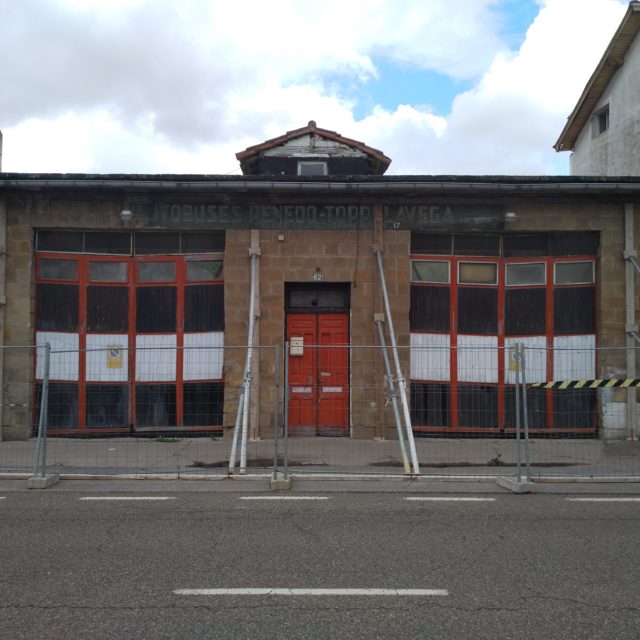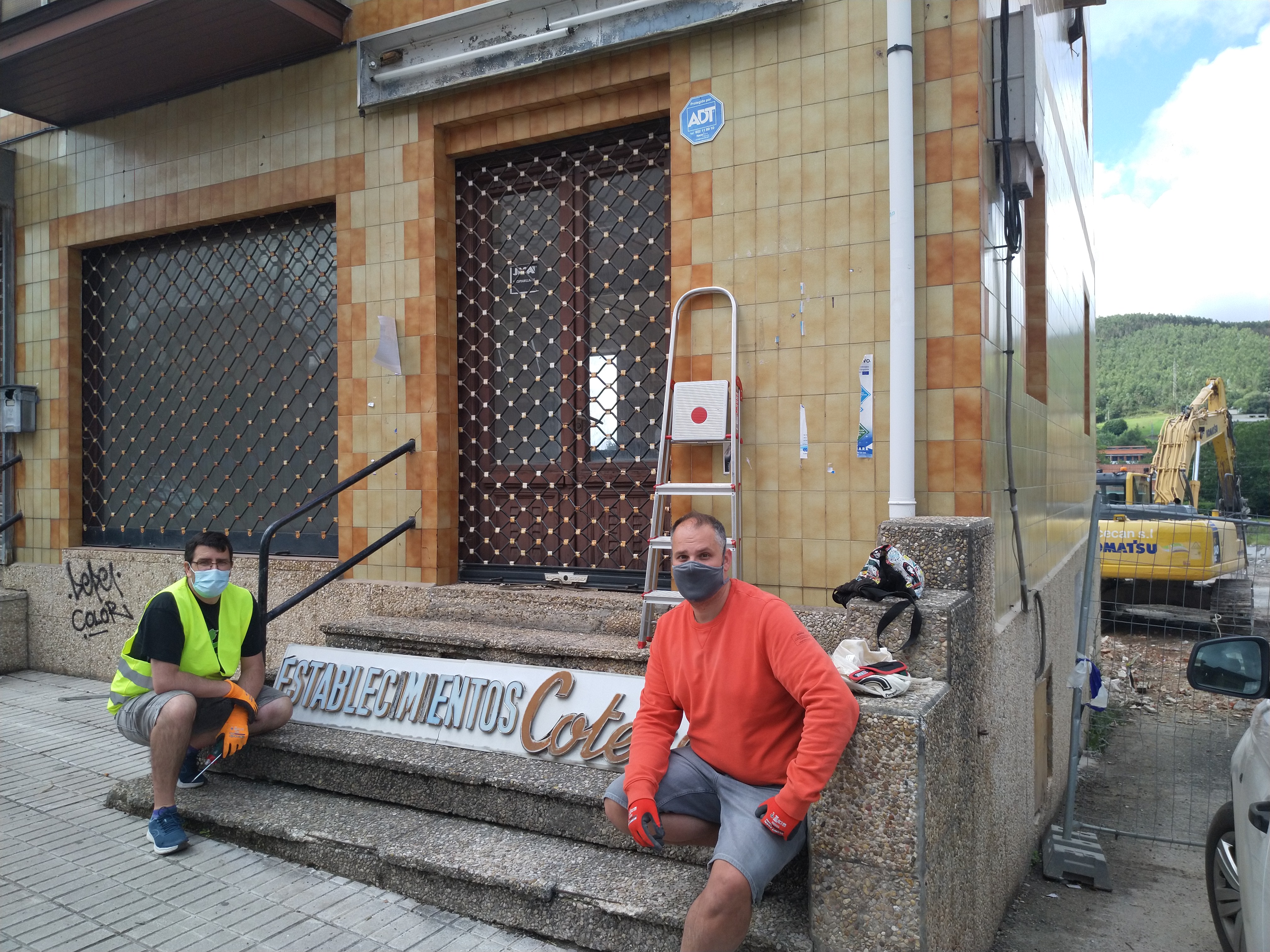
Establecimientos Coterón
La semana pasada nos avisaron de que en Renedo de Piélagos comenzaron las obras de demolición de los talleres de los “Autobuses Aranda Calderón” de los años 50 que conservaban el rótulo pintado en su fachada. Tras lanzar el #SOSPatrimonio pudimos acercarnos a verlo in situ. Al estar integrado no se ha podido salvar, pero si hemos podido documentarlo gráficamente.
Fachada antes de la demolición. Julio, 2021.
En el proceso de demolición, donde se ha preparado el terreno para la implantación de una cadena de supermercados, también se incluía una casa anexa que en su bajo estaba ubicado “Establecimientos Calderón”. Tienda de toda la vida, donde era habitual encontrar menaje y ferretería en el municipio. Pudimos bajar su rótulo hecho con dos tipografías (Palo seco y Script) montadas sobre una placa de plástico, que estaba bastante dañada.